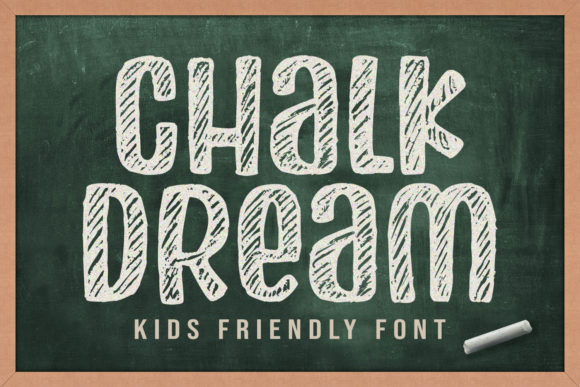
Chalk Dream
適切なデザイン要素を見つけるのは難しい場合がありますが、Chalk Dreamは作品を即座に引き立てる優れたコレクションを提供します。
POD(オンデマンド印刷)製品、結婚式の招待状、またはソーシャルメディアのグラフィックを作成している場合でも、Chalk Dreamは理想的です。